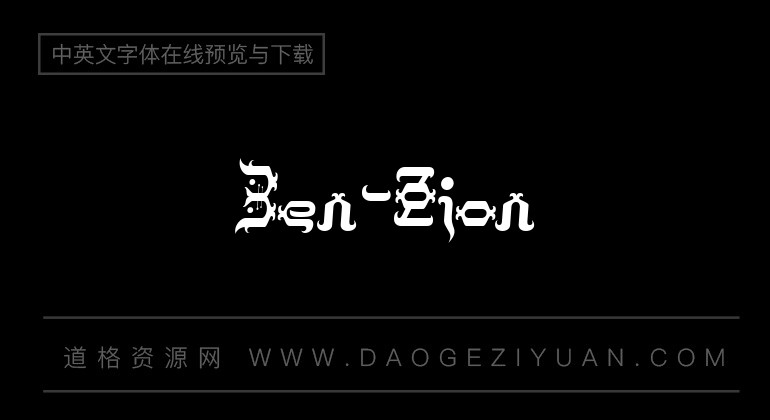
Ben-Zion
Ben-Zion 字体是由犹太裔美国设计师 Ben-Zion David 创作的一款英文字体。它是一种极具特色的衬线字体,字体的设计灵感来自于犹太文化,字体有着丰富的历史背景,给人一种充满神秘感的感觉。它的设计风格结合了传统的犹太文字和现代技术,使得字体可以更加灵活地应用于现代印刷品和网络文字中。它的特点是字体的结构紧凑,笔画细腻,线条流畅,使字体看起来更加精致。
Ben-Zion是一款非常不错的手写艺术字体,具有很好的视觉感,适合于文化类的宣传设计、商业类品牌的广告和产品包装设计以及个性化文字排版等较多场景。